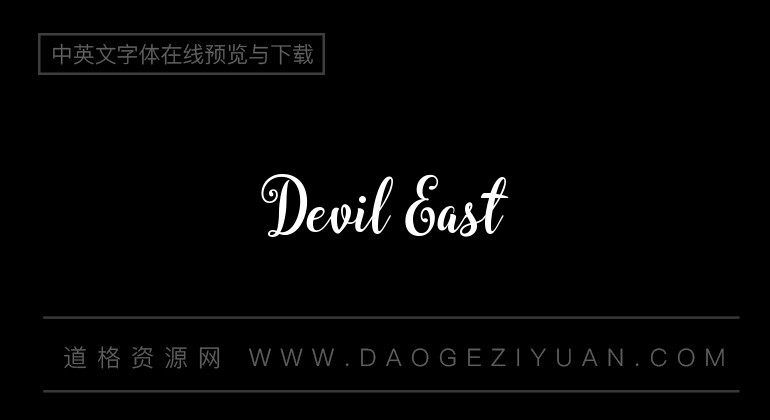
Devil East是一种艺术字体,具有东方风格的设计元素。它的字母形状较为复杂,线条优美流畅,展现出神秘、独特的气质。 这种字体的设计灵感来源于东方文化的符号和装饰,如龙、凤、云、花纹等。它通常使用在需要具有神秘、古老、神话的氛围的设计场景中,如影视片头、海报、书籍封面等。 该字体在设计领域中得到了广泛的应用,因为它能够让设计作品更具有视觉冲击力和独特性。内容介绍
Devil East是一款非常不错的手写艺术字体,具有很好的视觉感,适合于文化类的宣传设计、商业类品牌的广告和产品包装设计以及个性化文字排版等较多场景。